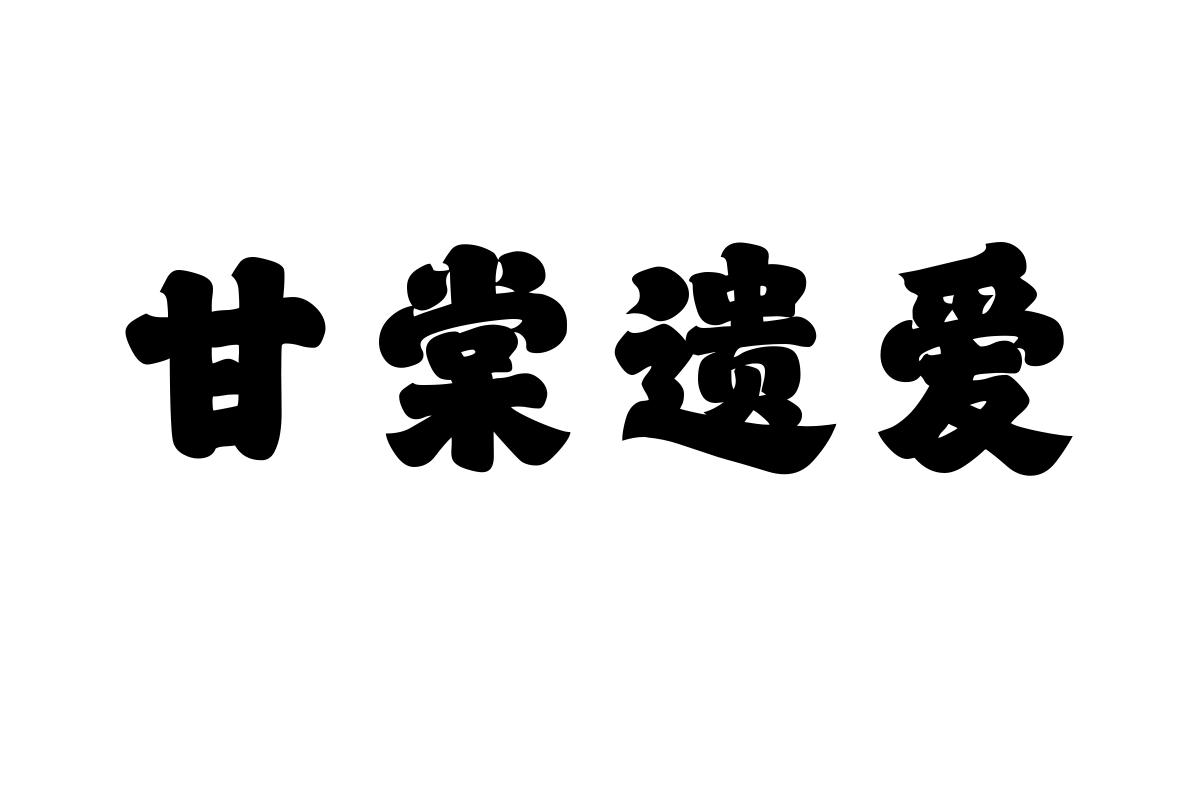
山海魁文榜书w 是一套具有独特艺术风格的字体,由设计师精心创作而成。这套字体以中国传统书法为基础,融入了现代审美元素,展现出一种独特的韵味和风格。
山海魁文榜书w 字体的特点如下:
1. 字形优美:山海魁文榜书w 字体的字形结构规整,线条流畅,给人一种优雅、大方的感觉。每个字的笔画都经过精心设计,使得整体字形更加和谐统一。
2. 艺术性强:山海魁文榜书w 字体在设计过程中充分考虑了艺术性,通过巧妙的笔触和布局,展现出一种独特的艺术美感。这种艺术性不仅体现在字形上,还体现在整体的排版效果上。
3. 适应性强:山海魁文榜书w 字体适用于各种场合,无论是用于书籍、杂志、广告还是网页设计,都能展现出其独特的魅力。同时,这套字体也具有较高的通用性,适合各种字体大小和风格的需求。
4. 文化内涵丰富:山海魁文榜书w 字体蕴含着丰富的文化内涵,体现了中国传统文化的独特魅力。通过对传统书法的借鉴和创新,使得这套字体既保留了传统韵味,又符合现代审美需求。
总之,山海魁文榜书w 字体以其优美的字形、艺术性强、适应性强以及丰富的文化内涵,成为了一款独具特色的字体。无论是作为个人作品还是商业用途,都能展现出其独特的魅力和价值。